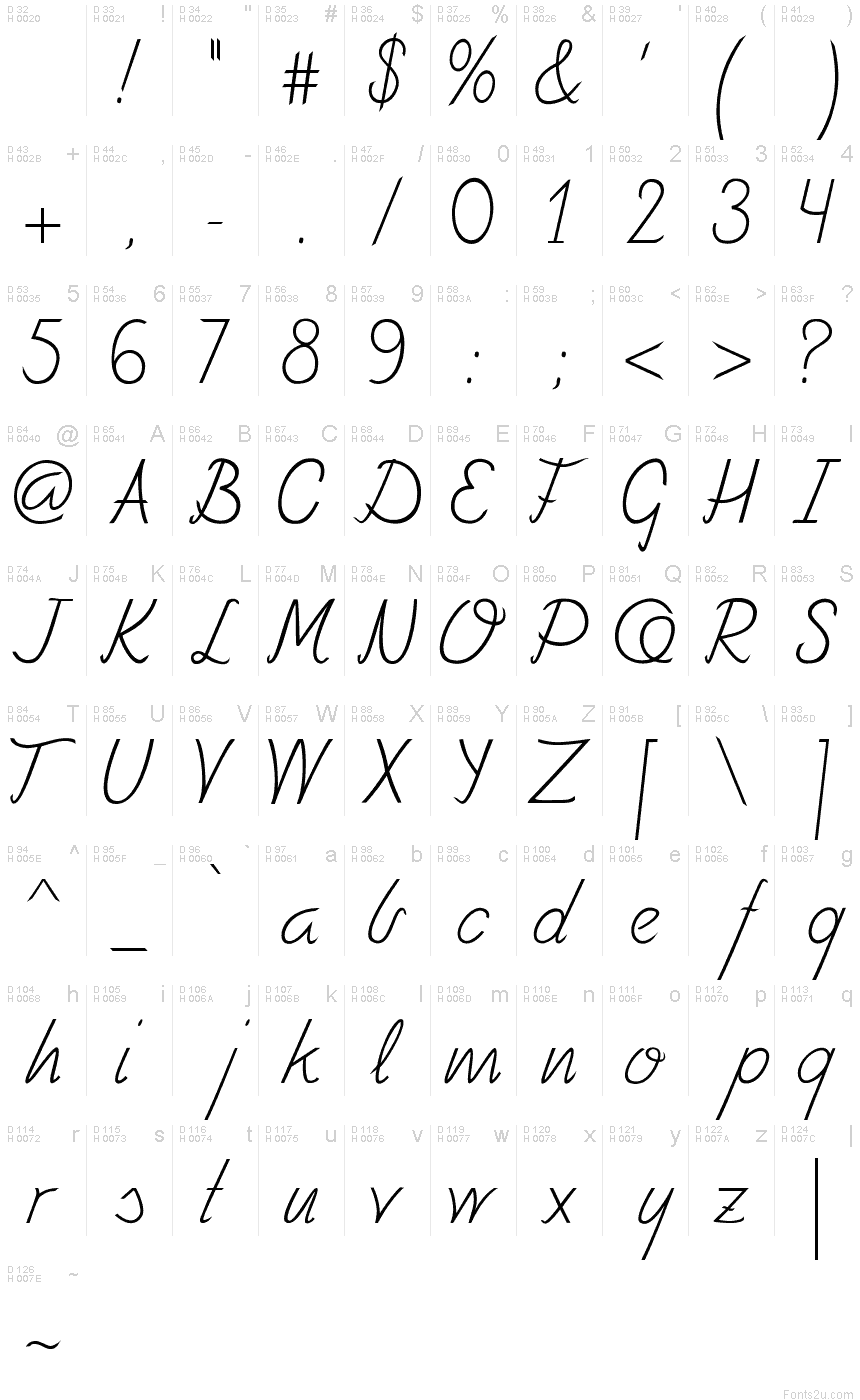
Fely هو خط يدوي مجاني يتميز بإيقاع خفيف وانسيابي. تتسم الحروف بحلقات طويلة وضربات ناعمة، مما يمنحه طابعاً رشيقاً وجذاباً يشبه التوقيع السريع أكثر من كونه خطاً كلاسيكياً رسمياً.
يعد هذا الخط مثالياً لعلامات المتاجر التجارية، وتغليف مستحضرات التجميل، وبطاقات الزفاف، وعناوين وسائل التواصل الاجتماعي، وأغلفة المجلات حيث تهم الحيوية والحركة. وبما أنه خط مجاني، فإن Fely يعمل بشكل رائع أيضاً مع العناوين والاقتباسات القصيرة والمونوغرامات، حيث تضفي الزوايا العالية والوصلات الدائرية إحساساً طبيعياً بالحركة على الكلمات القصيرة.
Fely